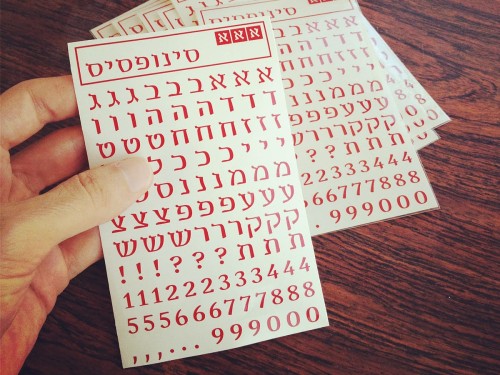
על אודות פונט סינופסיס
הוא מתפאר בסריפים שאפתניים, בעיקולים חושניים ובעושר צורני. כן, זהו סינופסיס, פונט תאטרלי וכריזמטי הנותן כבוד רב למסורת הכתב העברי ולאותיות הקלאסיות.
הפונט עבר תהליך התפתחות במשך יותר משלוש שנים, שבמהלכו נעשו בו אינספור בדיקות קריאוּת דקדקניות על מנת להפכו לאות־ספר – פונט המשמש לכתיבת טקסטים ארוכים וקריאים.
סינופסיס מאופיין באותיות יציבות במיוחד ובמשפחה ענפה בעלת משקלים מגוונים ושימושיים.
עוד ממאפייני הפונט: אנכי־האות (הגבעולים) עבים יותר מגגות־האות; האותיות מעט גבוהות מגובה ה־X; והוא מותאם לתצוגה על מסכים. כל אלה מאפשרים לו להרגיש בנוח לצד פונט לטיניים סריפים ולא לחשוש שמא יאפילו עליו.
בעל קריאות גבוהה, אפילו בגודל 4pt.